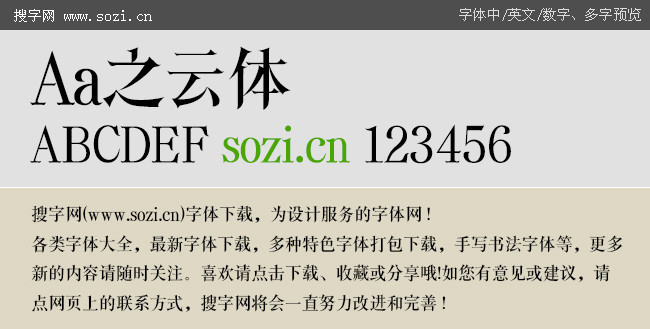
Aa之云體
搜字網(wǎng)給大家提供一款A(yù)a之云體(非商業(yè)使用)中文字體下載,Aa之云體是Aa字庫推出的一款個(gè)性藝術(shù)字體,該字體的每一個(gè)筆畫都非常的嚴(yán)謹(jǐn)、工整且大氣,適應(yīng)于報(bào)紙、雜志、書籍、海報(bào)設(shè)計(jì)等應(yīng)用(此字體為個(gè)人非商用版,商用可以聯(lián)系QQ:1006760504)。